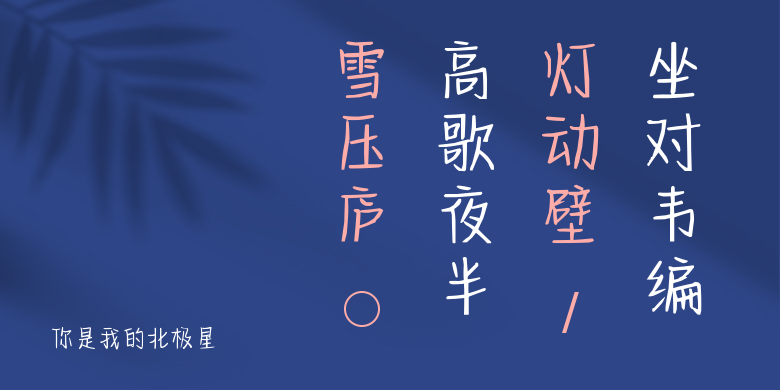
你是我的北极星
你是我的北极星,这款字体结构工整、笔画清晰,兼顾美观与易读性,适用于标题、正文、海报、包装、LOGO 等多种场景。字形优雅稳定,风格百搭耐看,适配日常排版与创意设计,让文字呈现更舒适、更具质感。你是我的北极星一笔一画,皆是细节,以均衡的比例、流畅的线条打造舒适视觉体验,字形端正大气,风格简约现代。无论是商业设计、品牌宣传还是日常排版,都能轻松驾驭,让文字更有格调与力量。你是我的北极星字体下载。